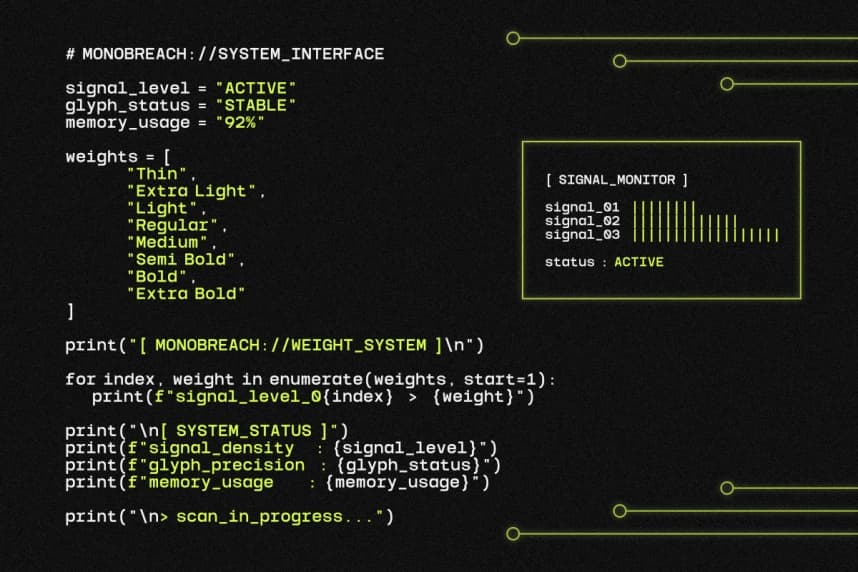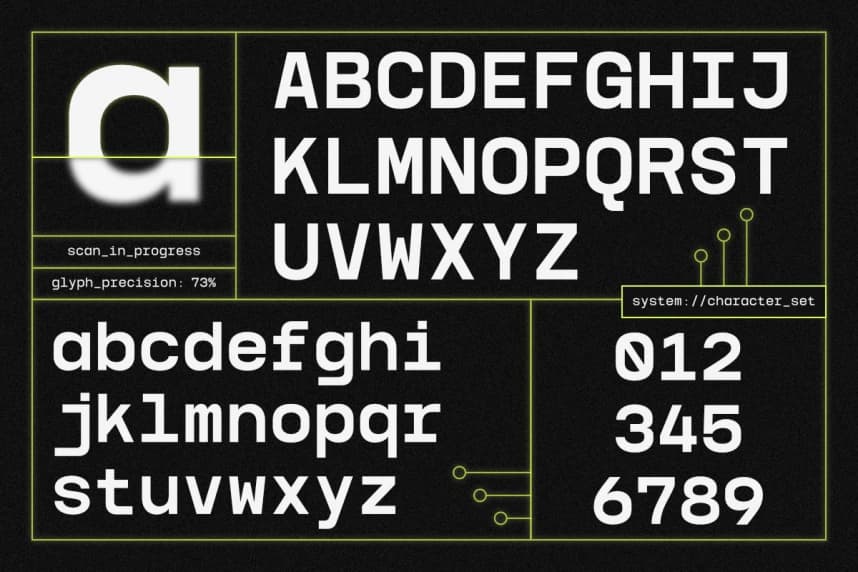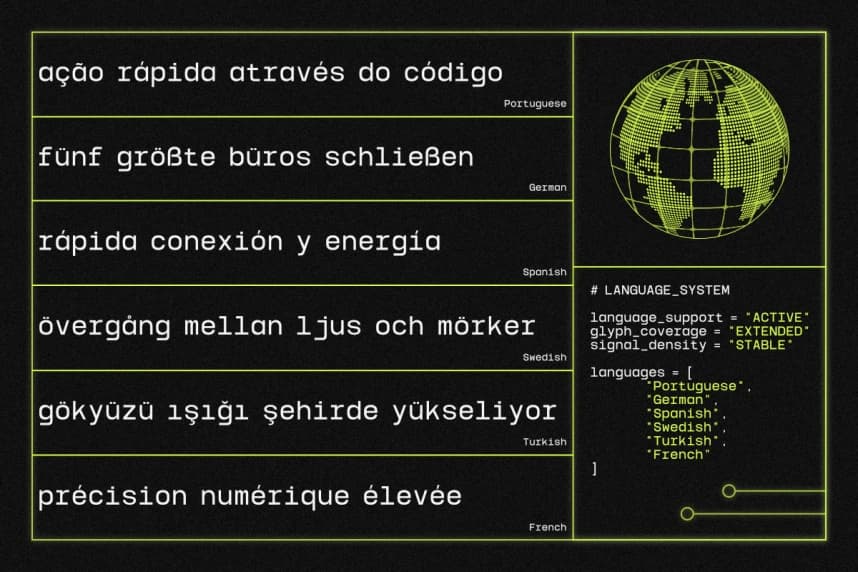
NV Monobreach Modern Monospace Yazı Tipi Ailesi
NV Monobreach Monospace Font Family, teknik netliği cesur görsel karakterlerle birleştirmek üzere tasarlanmış fütüristik ve hassasiyete odaklı bir yazı tipi sistemi olup NovaraType tarafından geliştirilmiştir. NV Monobreach, geometrik yapılandırma ve eşit aralıklar sunar.
NV Monobreach Monospace Font Family, teknik netliği cesur görsel karakterle birleştirmek üzere tasarlanmış fütüristik ve hassasiyete odaklı bir yazı tipi sistemidir. NovaraType tarafından geliştirilen NV Monobreach, geometrik yapı ve eşit aralıklar özelliklerine sahiptir